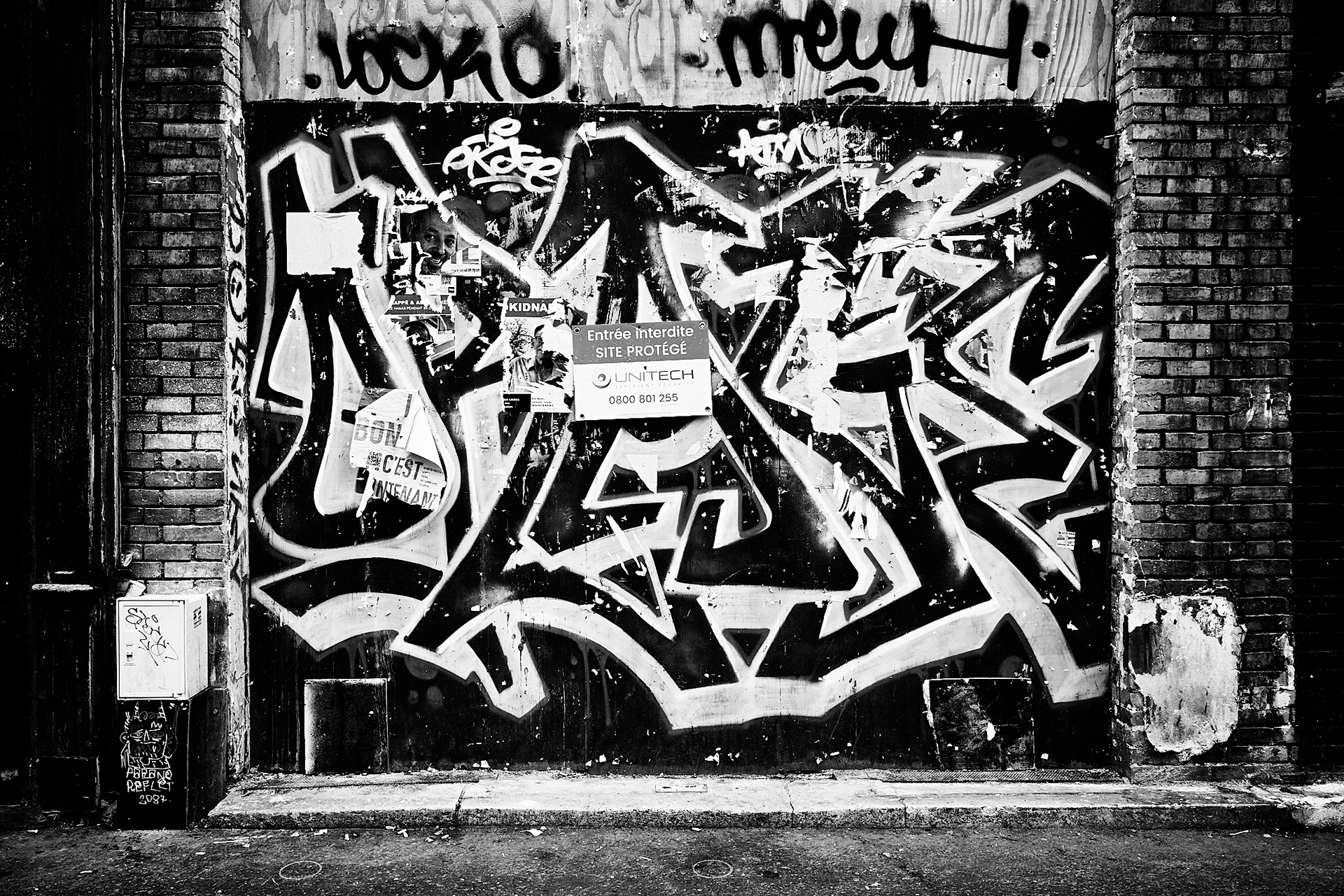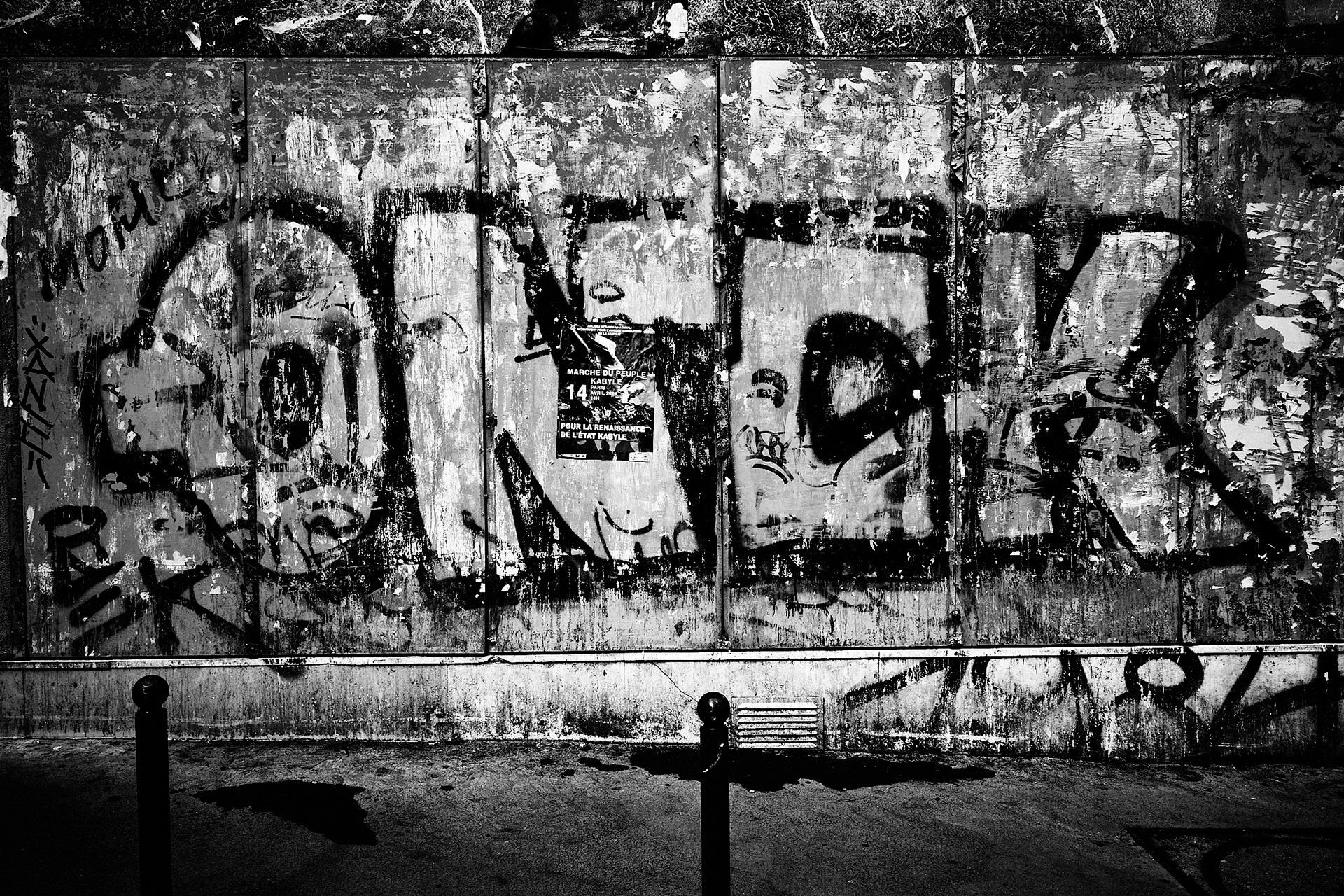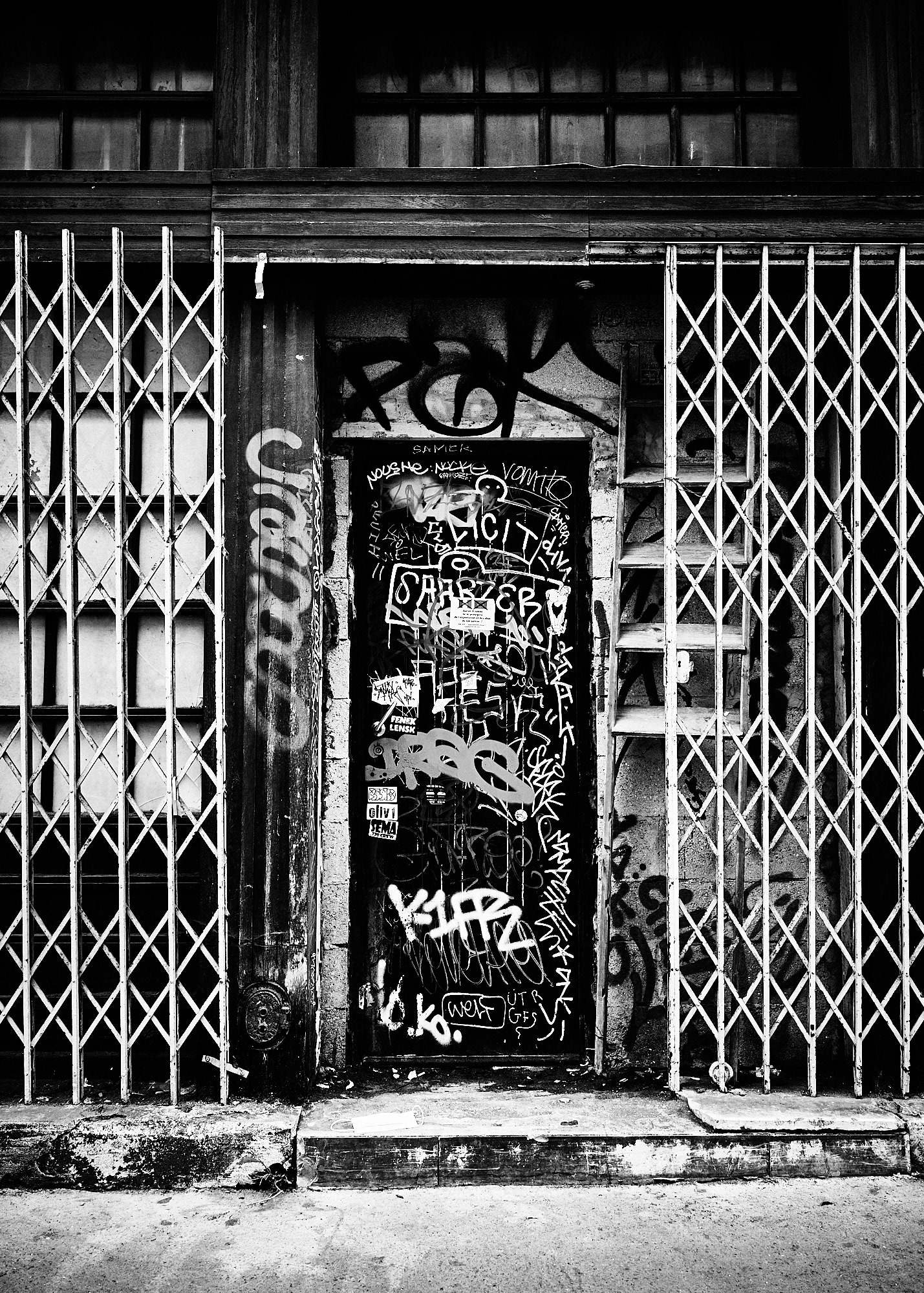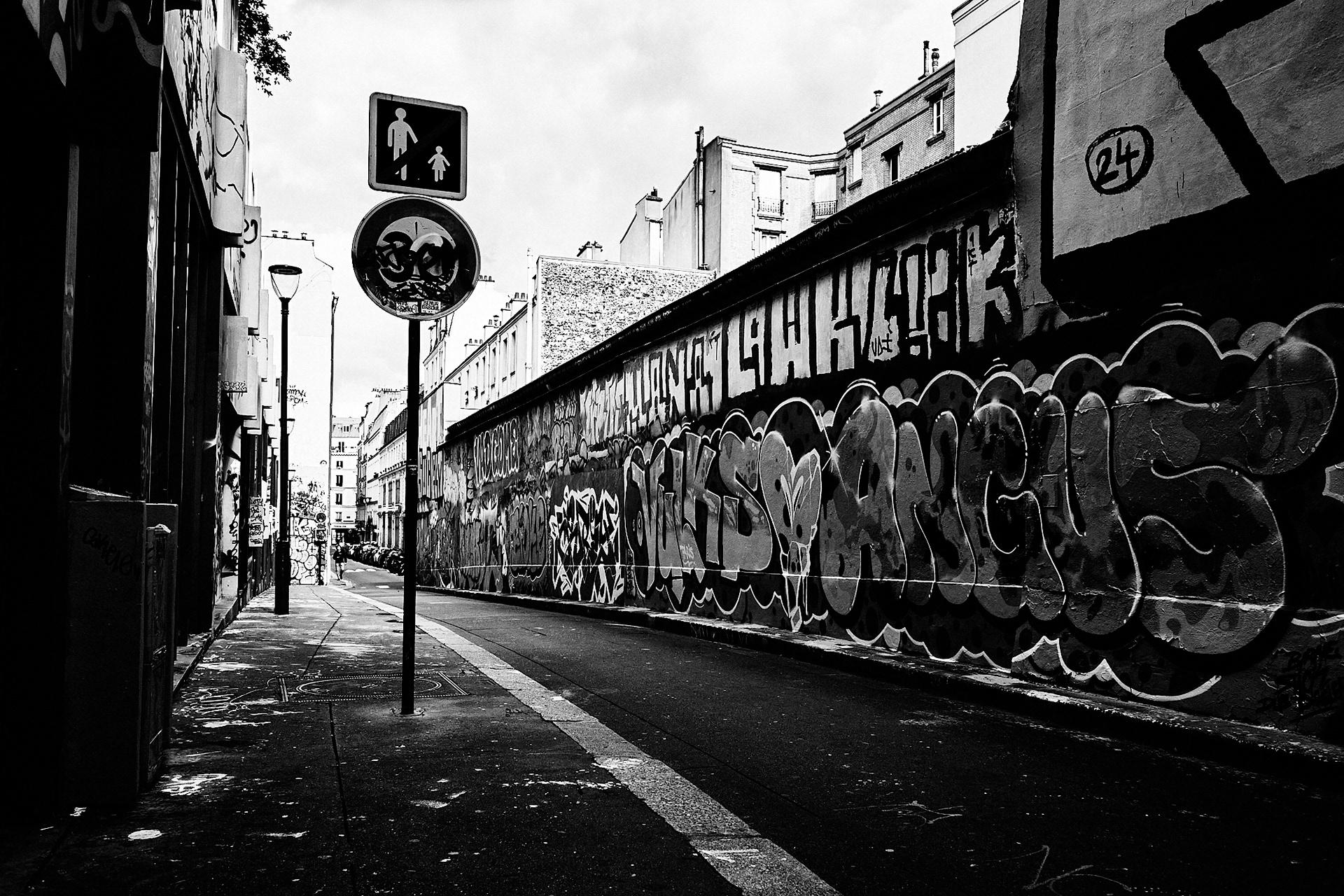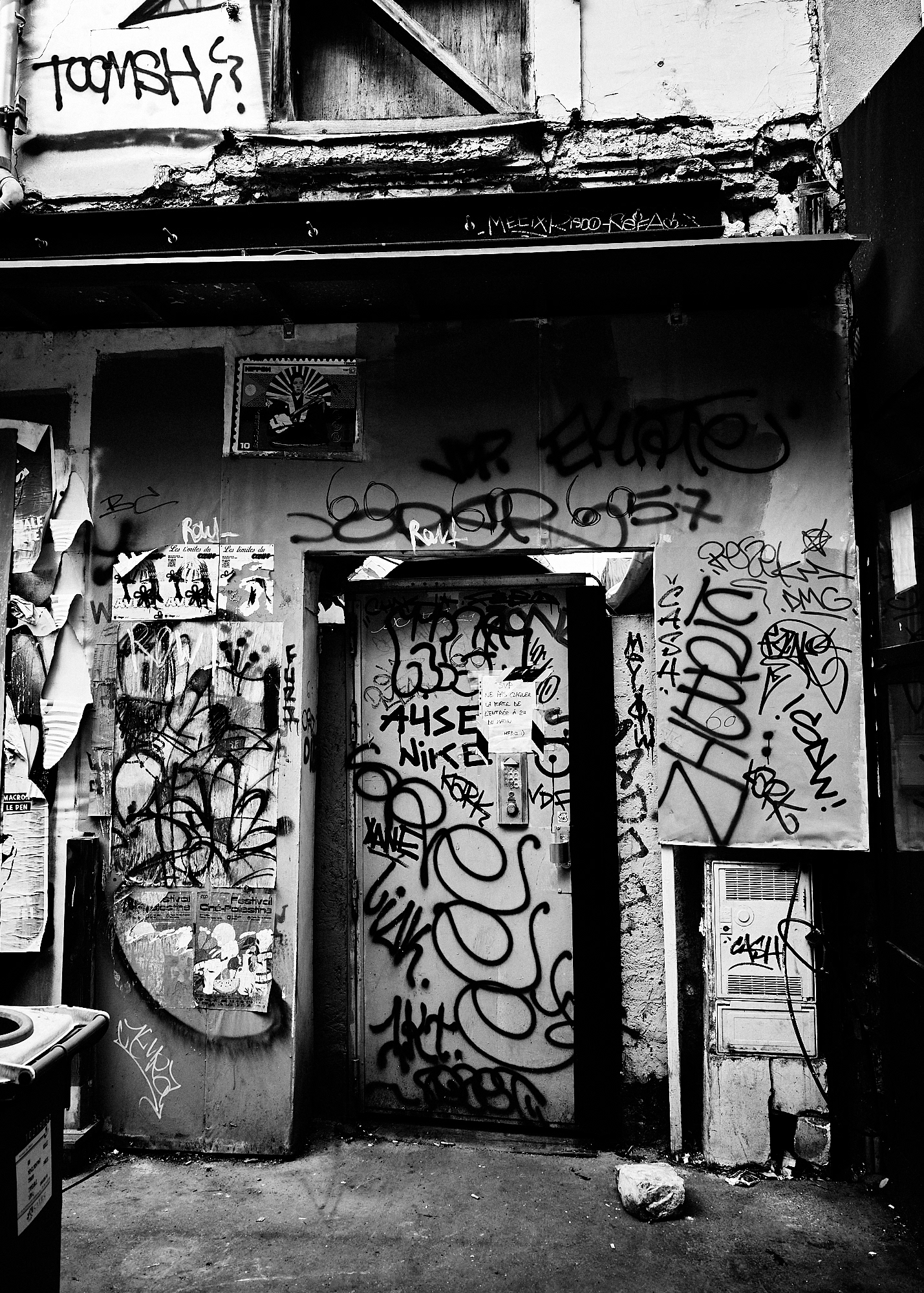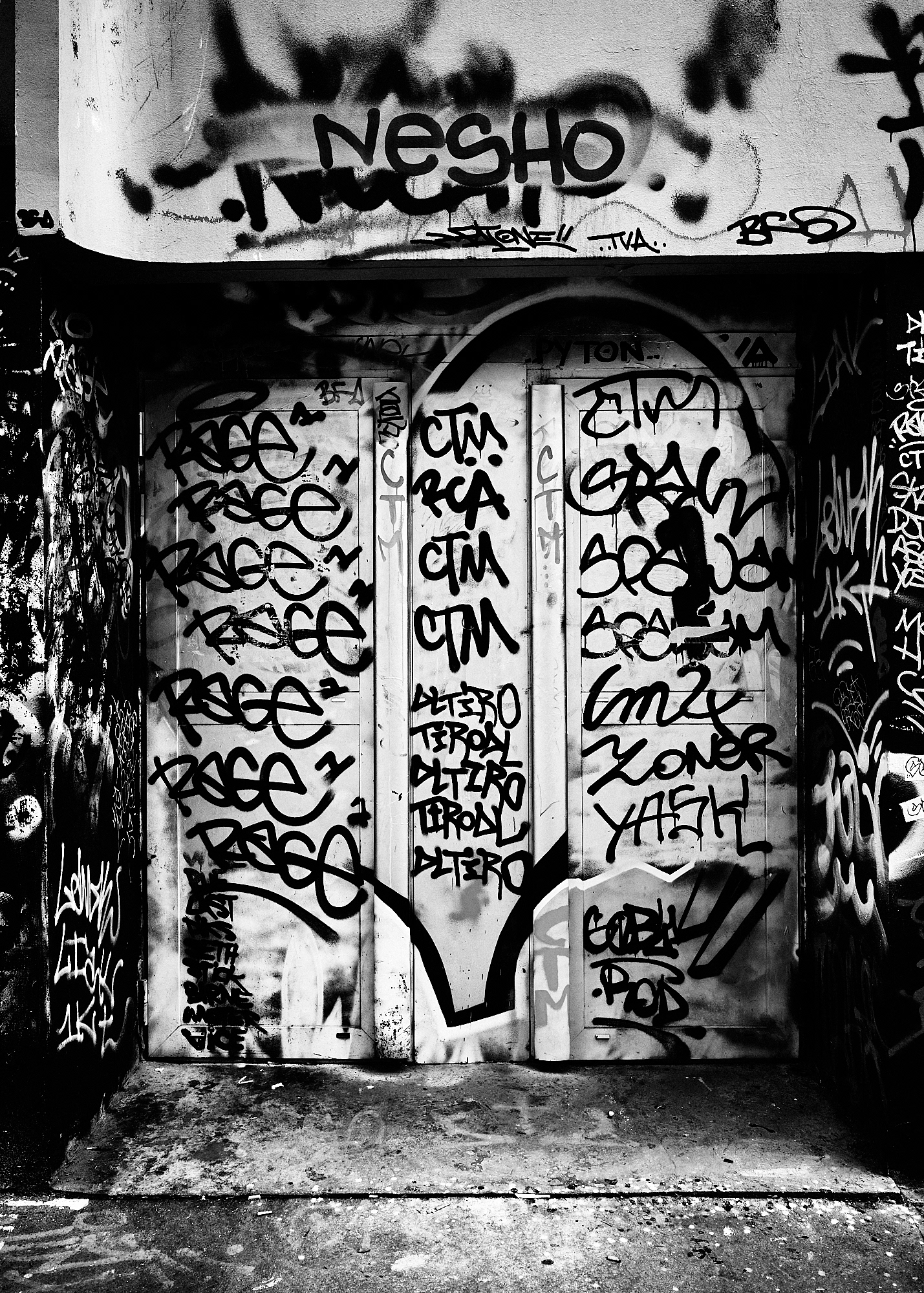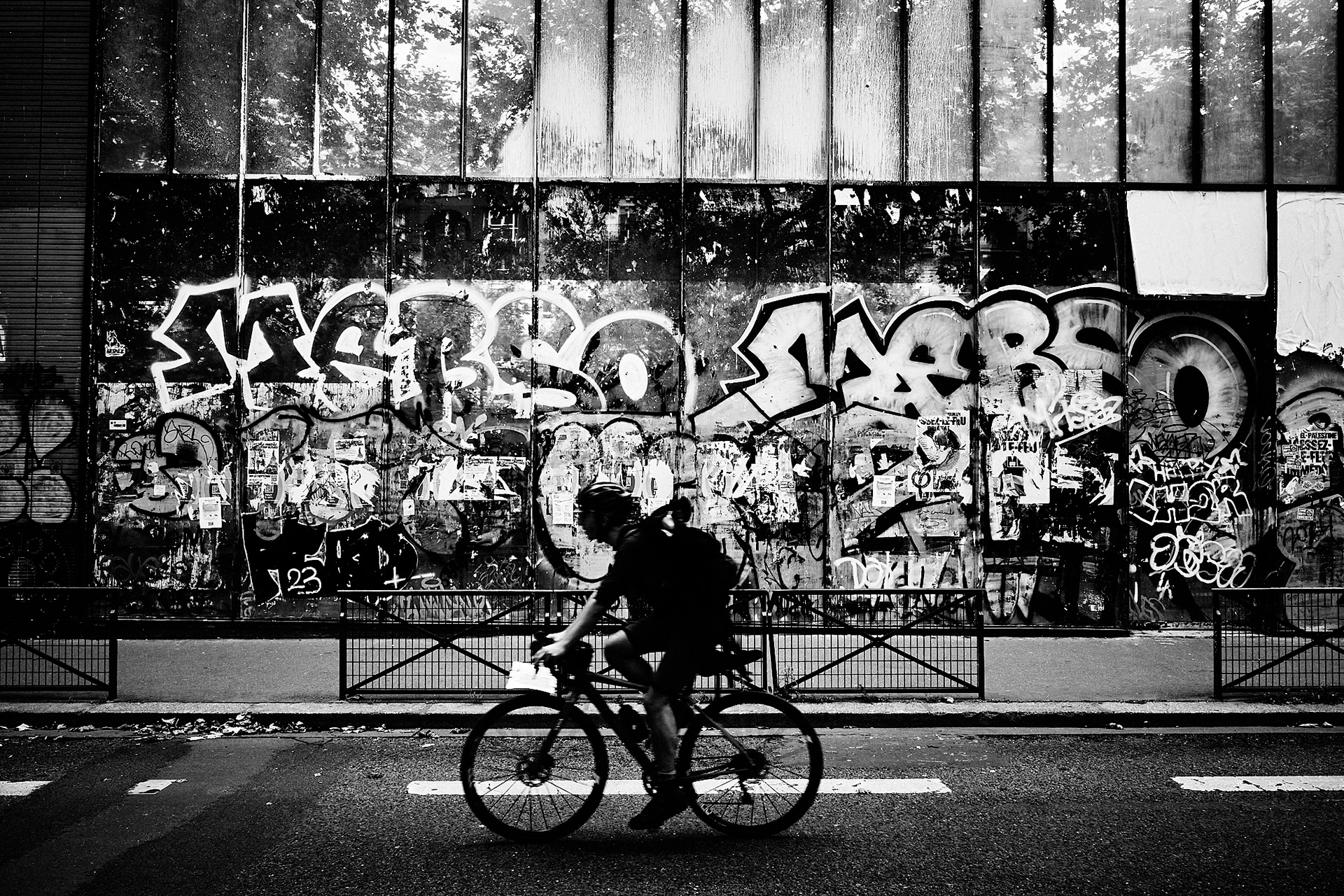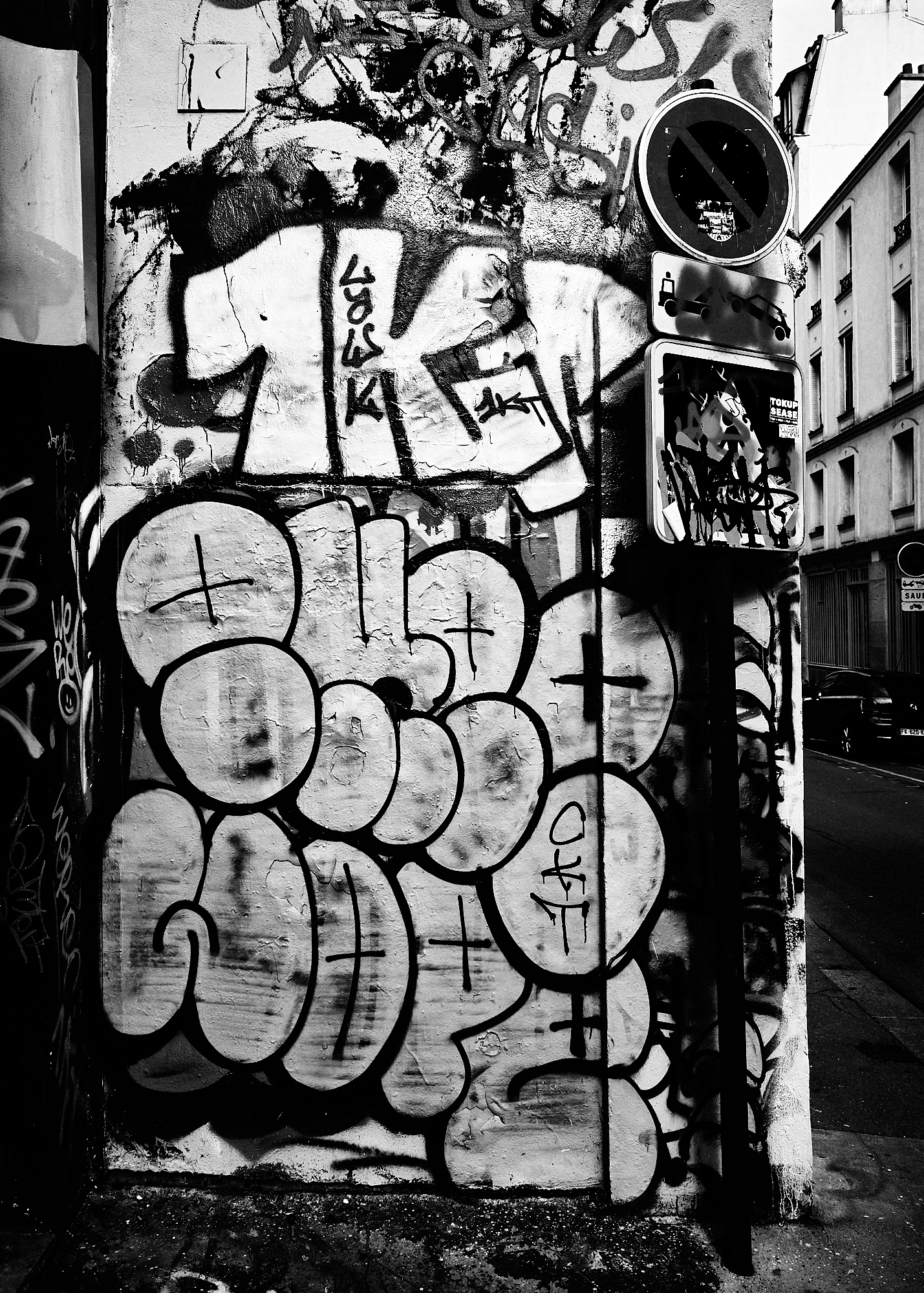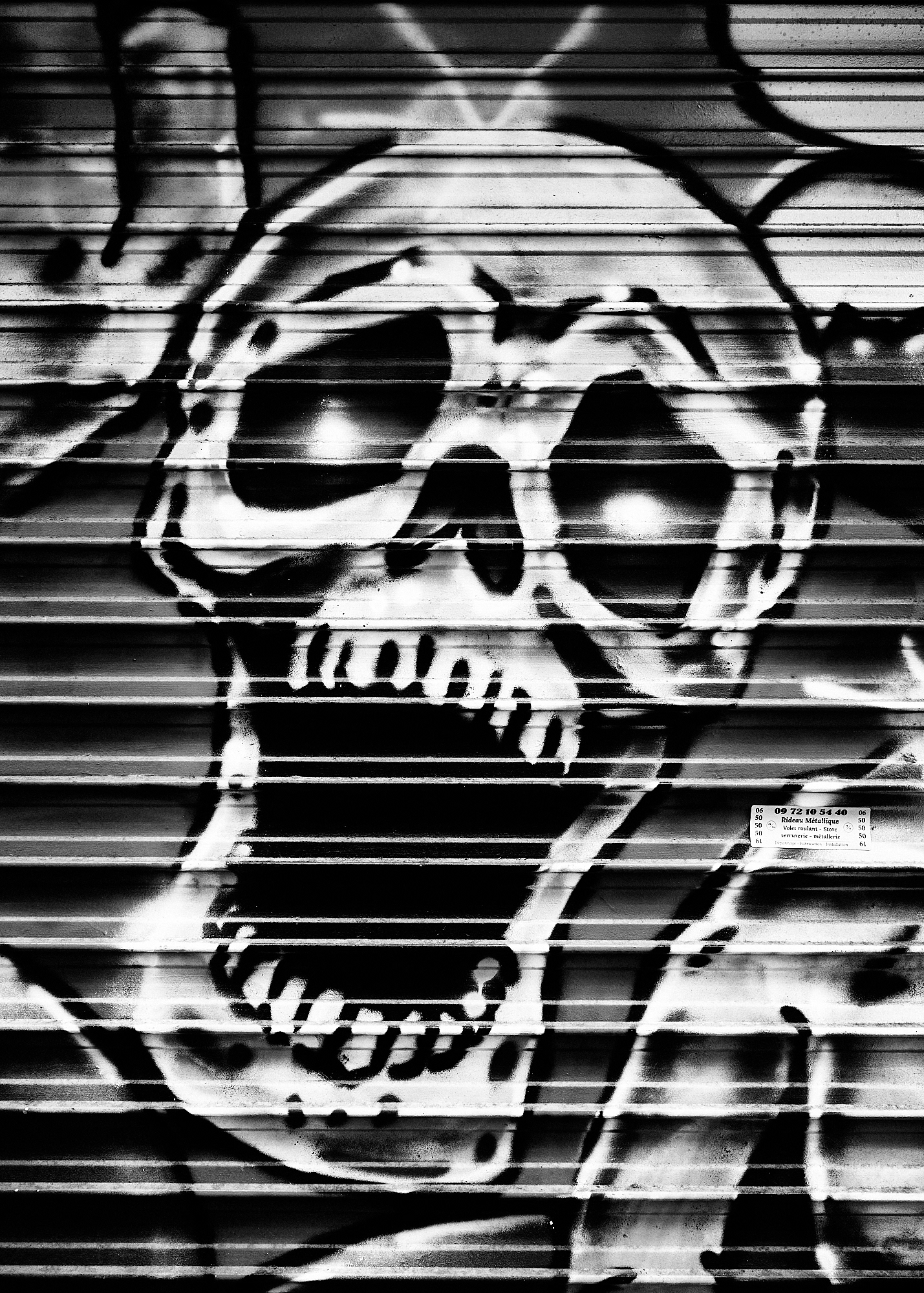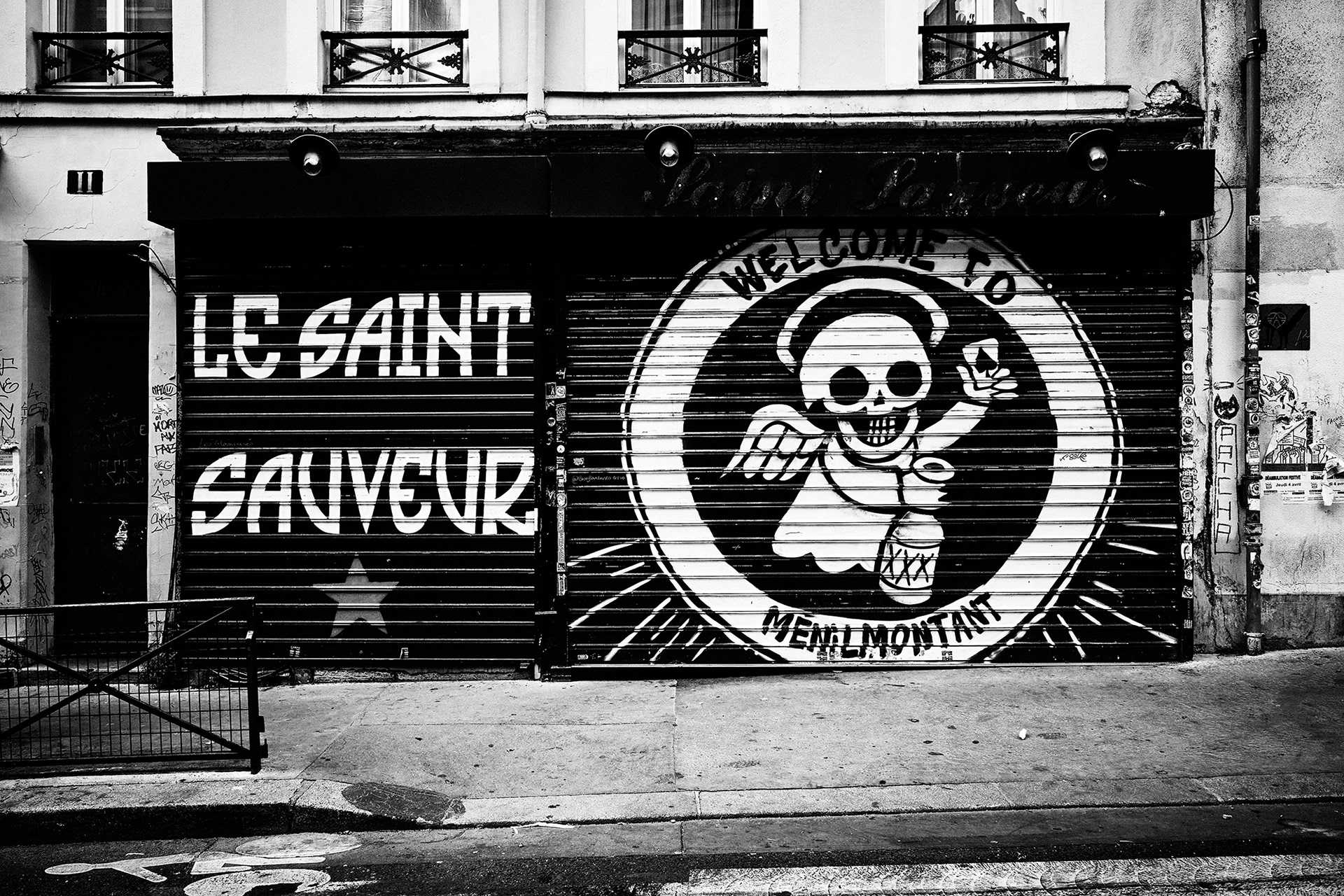
Les rideaux de fer tombent comme des pages que l'on tourne, les chaines cadenassées musèlent les portes. La ville se barricade et reste close derrière un rempart de lames et de grilles de fer. Le bitume devient chemin de ronde ou rue de révoltes.
Vieilles affiches usées par le temps et calligraphies alternatives s'imposent à notre regard. Dans un dédale de pierres et de béton, chaque façade livre ses messages abstraits suggérant quelques histoire, de l'inquiétude, si ce n'est la colère.
Entre ombre et lumière se dessine alors un récit sans fin. À chaque coin de rue nait une nouvelle intrigue et le suspens est à son comble. Les murs de la ville se lisent alors comme les pages déchirées d'un vieux roman noir.